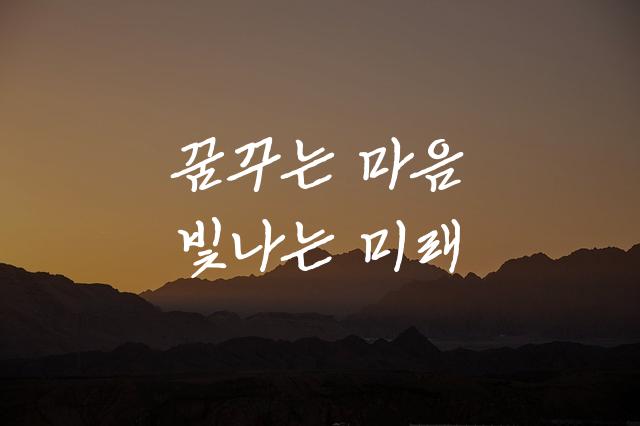
KCC차쌤체는 한국저작권위원회에서 제작한 폰트로, 또박또박한 어른의 손글씨를 바탕으로 디자인되었습니다. 따뜻하고 친근한 감성을 담아 일상의 소통을 더욱 풍부하게 만듭니다.
KCC차쌤체은(는)
바탕 스타일, 손글씨, 감성적인, 부드러움 계열의 생김새를 가지고 있으며
교육 자료, 어린이 책 등에서 자주 활용되며, 효과적인 메시지 전달에 적합합니다.
이 폰트는 교육, 유아/가족 분야에 잘 어울리며,
친근한, 귀여운 느낌을 담고 있는 것이 특징입니다.